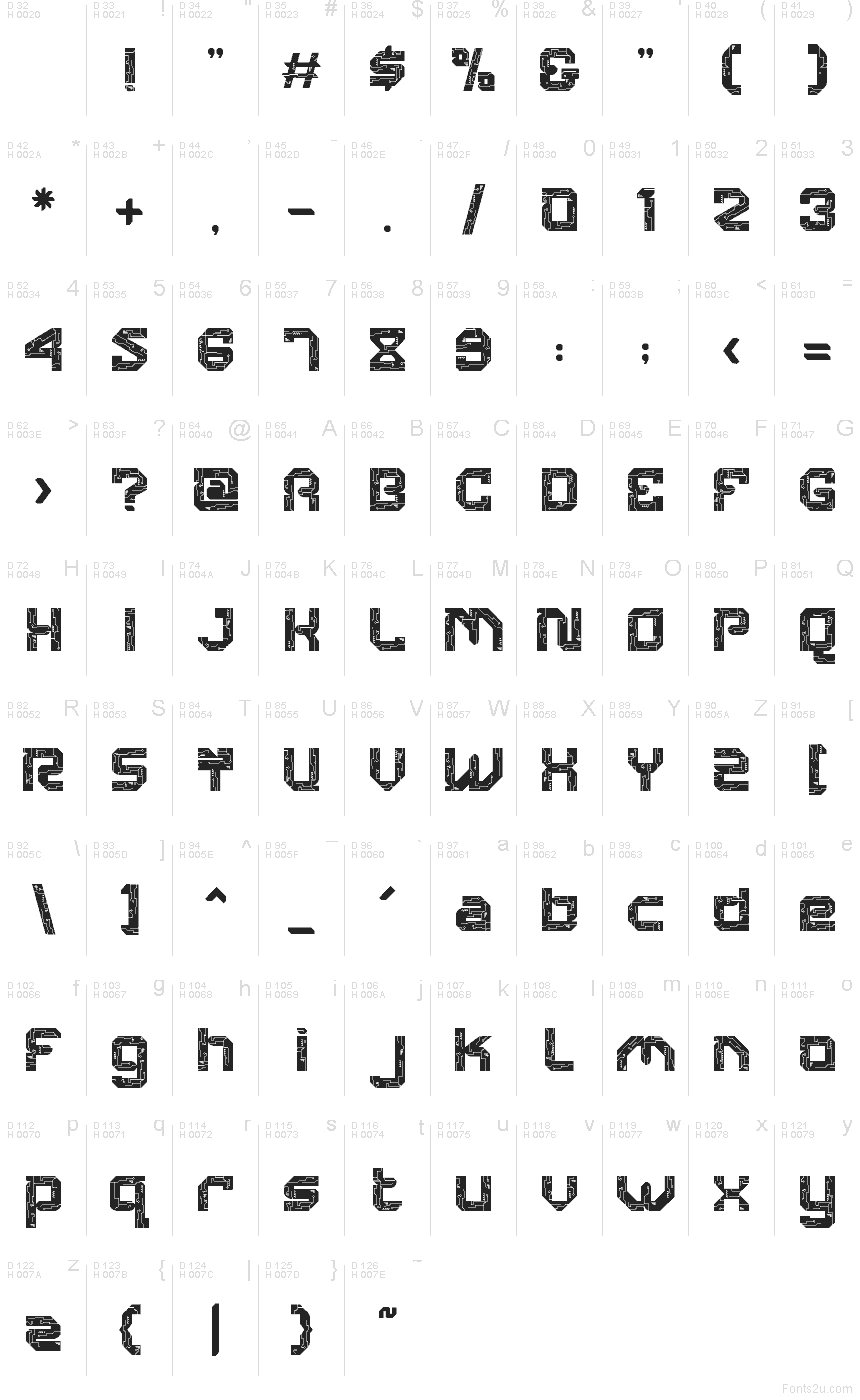
Cyber Crown Three od Putracetol Studio je bezplatné písmo inspirované plošnými spoji. Písmena jsou protkána trasovacími linkami, malými uzly a hranatými cestami, které připomínají grafiku základních desek. Tento opakující se elektronický motiv dává designu hustou, technickou texturu, takže písmo nepůsobí jako běžný futuristický nápis, ale spíše jako značení vytažené přímo z hardwarového rozhraní.
Nejlépe vynikne u herních titulů, plakátů na technologické akce, sci-fi brandingu, streamer grafiky a obalů gadgetů, kde tyto detaily obvodů mohou skutečně podpořit dané téma. Zvláště krátké nadpisy, loga a sekční značky z něj těží nejvíce, protože vnitřní vzor cest dodává i několika málo znakům dostatečnou výraznost, aby orámovaly digitální prostředí.